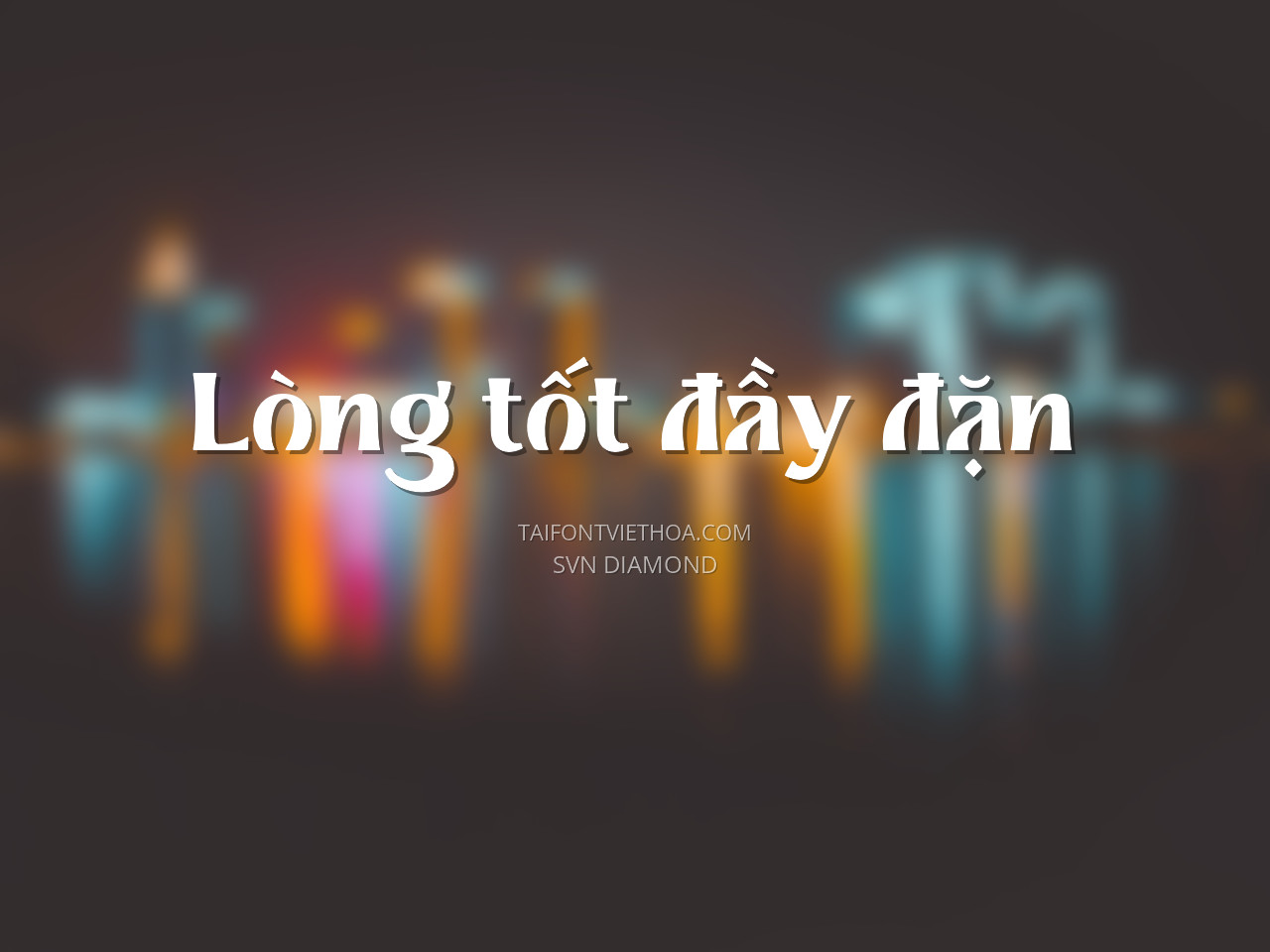
Giới thiệu về font SVN Diamond – Kiểu chữ serif sang trọng, đẳng cấp và tinh tế
SVN Diamond là phiên bản Việt hóa của font Diamond – một kiểu chữ serif mang phong cách sang trọng, đẳng cấp với các nét chữ sắc sảo, cân đối và chi tiết tinh tế. Font được thiết kế nhằm tạo nên sự tinh tế, chuyên nghiệp và phù hợp cho các dự án thiết kế thương hiệu, in ấn và truyền thông cao cấp.
Phiên bản Việt hóa của SVN Diamond đã được Taifontviethoa.comchăm chút kỹ lưỡng, hỗ trợ đầy đủ dấu tiếng Việt cùng hơn 80 ngôn ngữ khác. Font giúp các nhà thiết kế dễ dàng áp dụng trong nhiều sản phẩm đa dạng mà vẫn giữ được vẻ đẹp sang trọng và tinh tế.
Thiết kế serif tinh tế – Ứng dụng rộng rãi trong thương hiệu và xuất bản
SVN Diamond sở hữu cấu trúc serif với các nét chữ thanh mảnh, đường cong uyển chuyển và độ tương phản hài hòa. Font phù hợp cho đoạn văn bản dài và tiêu đề, giúp tăng tính thẩm mỹ và sự chuyên nghiệp cho thiết kế. Phong cách của Diamond mang đến sự trang nhã và đẳng cấp cho mọi sản phẩm thiết kế.
Ứng dụng lý tưởng: thiết kế nhận diện thương hiệu, bìa sách, tạp chí, brochure, thư mời, danh thiếp và các ấn phẩm quảng cáo cao cấp. Ngành nghề phù hợp: thời trang, mỹ phẩm, nội thất, giáo dục, xuất bản và các thương hiệu định vị theo phong cách sang trọng, tinh tế.